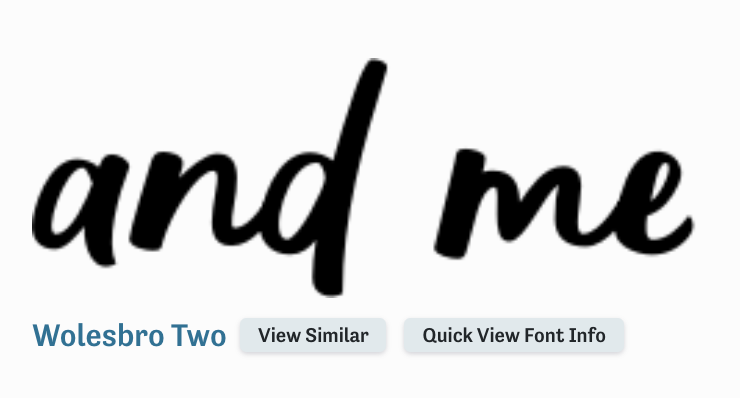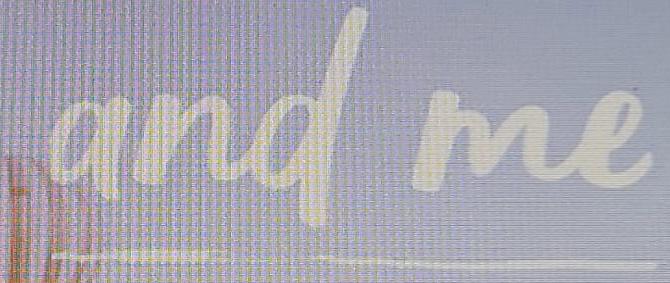
Handwritten Font aus one.com?
Die Schrift wurde vermutlich in einem Template generiert bei one.com? Leider kann ich das nicht nachvollziehen, obwohl ich ich mich dort schon angemeldet habe. Ich dachte erst, es ist die Caveat, weil die auch sonst dort Googlefonts nutzen, aber die sieht drübergelegt doch nur ähnlich aus. Hat jemand eine Idee? WTF und Whatfontis haben mir nicht geholfen.
Und ein Tip für Whatfontis und andere Font-Erkenner: DieseProgramme können die Buchstaben mir mit den kinterlegten Mustern vergleichen, wenn dieseBuchstabebn einzeln auch frei stehen. Sobaldaber die Buchstaben sich irgendwie überlappe, wie hier bei  "nd"und "me" wird dies alsquasi ein Zeichen erkannt,und das kommt dann auch in der Vergleichs.Liste nicht vor,und der Font kann nicht erkannt werden.
Darum finden sich soche Handschriftfontsauch selten unter dem Vergiechsmaterial, da hier oft ganze Worte ein zusammenhängendes Zeichen gilden, und man hann da nicht für jede Schrift alle möglichen Worte hinterlegen, Andererseits ist es selbst für die beste KI kaum moglich zu erkennen,wie hier die Buchstaben voneinander zu trennen sind.
Also bleibt nur, das zur Erkennung vorhandene Muster  doppelt hinter einander zu setzen, und dann in einer Bildbearbeitung jeden 2. Buchstaben ( von der 2.Kope dann die geraden Buchstaben) heraus zu löschen (so dass aus dem Beispiel hier "a d m n e "wird,und dabei möglichst zu erraten, wie wohl der überlappende Teil unter  dem zu löshenden Buchstaben wohl genau geformt ist. n und m hier dürften noch eine kleine Rundung  unter  d und e "geschoben" haben, währens d und r wohl  links glatt vom Vorbuchstaben abzutrennen ist.
Oft, aber nicht immer  ist so dann eine automatische Erkennung möglich